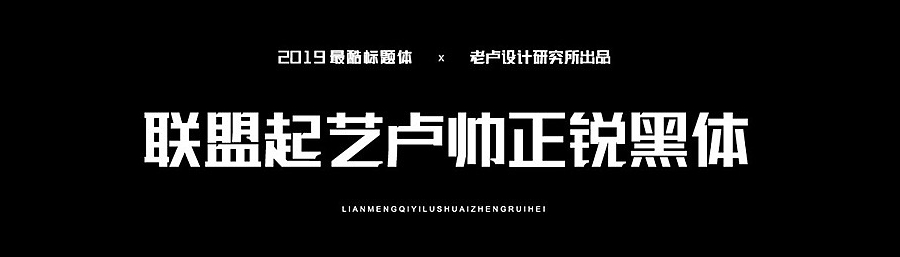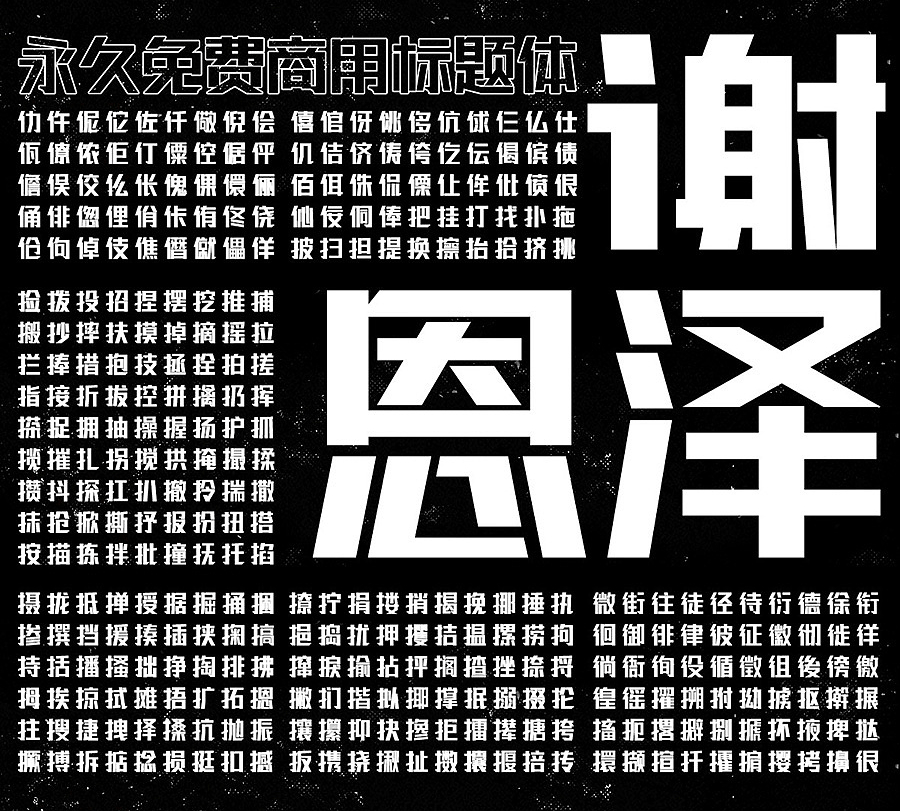
聯盟起義盧帥正銳黑體共計8000餘字,永久免費商用標題體!字庫團隊骨幹設計師:凌旬(徐文博)、子軒、璐過炒米(李璐)、尚偉、小呆瓜(黃鑫)、獅子(郭培晟)、呂少惠
一款免費字體並不能改變世界甚麼,但希望我們的努力,能讓“初心”重新迴歸到我們自己心中正確的位置。我們希望帶給剛步入設計行業為字體版權頭痛的你,正在設計行業沉淪為字體版權踟躕的你,喜歡美好熱愛生活的你,帶來一次小小的感動。